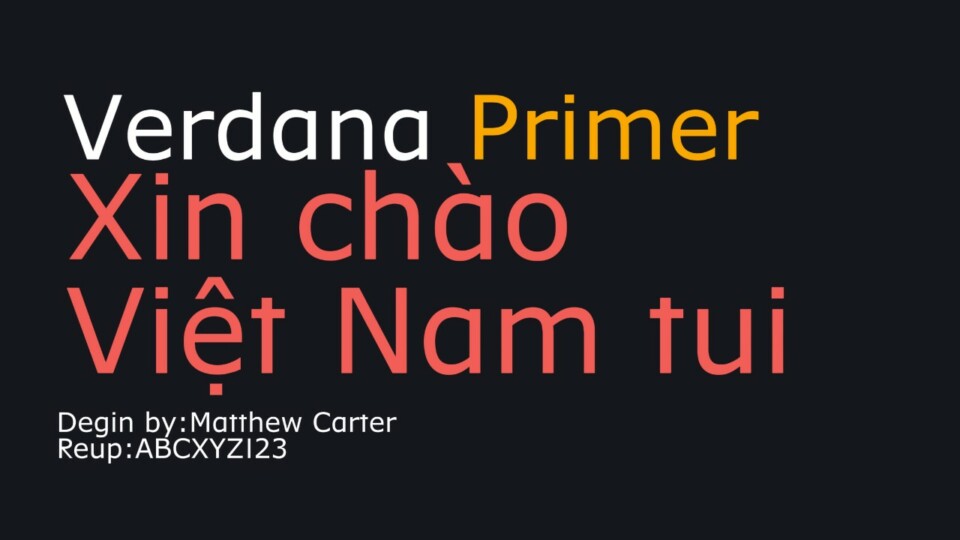
Font Verdana Primer (Gõ Tiếng Việt) – Bộ Phông Chữ Học Đường Hoàn Hảo
Giới thiệu về Font Verdana Primer (Gõ Tiếng Việt)
Trong môi trường giáo dục tiểu học, việc lựa chọn một Font Chữ chuẩn mực để soạn thảo giáo án và bài tập là vô cùng quan trọng. Font Verdana Primer (Gõ Tiếng Việt) được thiết kế đặc biệt nhằm đáp ứng nhu cầu học tập và giảng dạy tại Việt Nam. Đây là phiên bản cải tiến từ phông chữ Verdana truyền thống, tập trung vào sự rõ ràng, dễ đọc và hỗ trợ đầy đủ các dấu thanh đặc trưng của tiếng Việt.
Đặc điểm nổi bật của bộ font
Đặc trưng lớn nhất của Font Verdana Primer (Gõ Tiếng Việt) chính là khoảng cách giữa các chữ cái được tối ưu hóa, giúp học sinh dễ dàng phân biệt mặt chữ mà không bị mỏi mắt. Các nét chữ được tinh chỉnh thanh thoát, không quá dày nhưng vẫn giữ được sự chắc chắn. Điều này giúp bộ font trở thành lựa chọn ưu tiên cho các tài liệu in ấn và trình chiếu trong lớp học.
Lợi ích khi sử dụng Font Verdana Primer (Gõ Tiếng Việt)
Sử dụng Font Verdana Primer (Gõ Tiếng Việt) giúp đồng bộ hóa các tài liệu giảng dạy một cách chuyên nghiệp. Phông chữ này tương thích tốt với các bộ gõ phổ biến như Unikey hay VietKey, đảm bảo không xảy ra lỗi hiển thị khi đánh máy các từ có dấu phức tạp. Ngoài ra, tính thẩm mỹ cao của font còn giúp kích thích sự hứng thú trong việc đọc viết của trẻ em.
Tính ứng dụng linh hoạt
Không chỉ giới hạn trong trường học, bộ font này còn được các nhà thiết kế ưa chuộng khi làm sách thiếu nhi hoặc ứng dụng giáo dục trực tuyến. Sự hiện đại xen lẫn nét cổ điển tạo nên một phong cách trình bày văn bản khoa học và tinh tế.
Kết luận về bộ font học đường